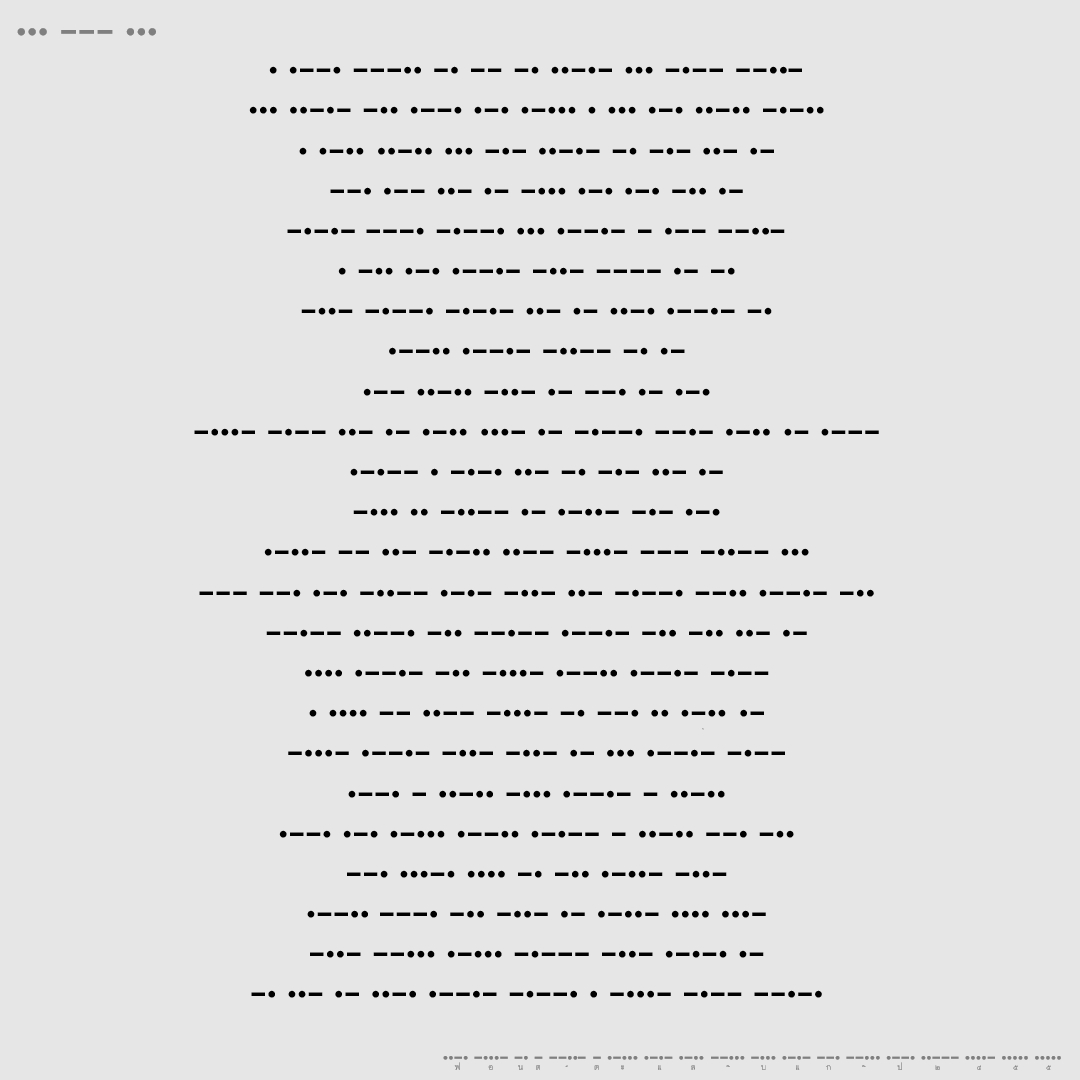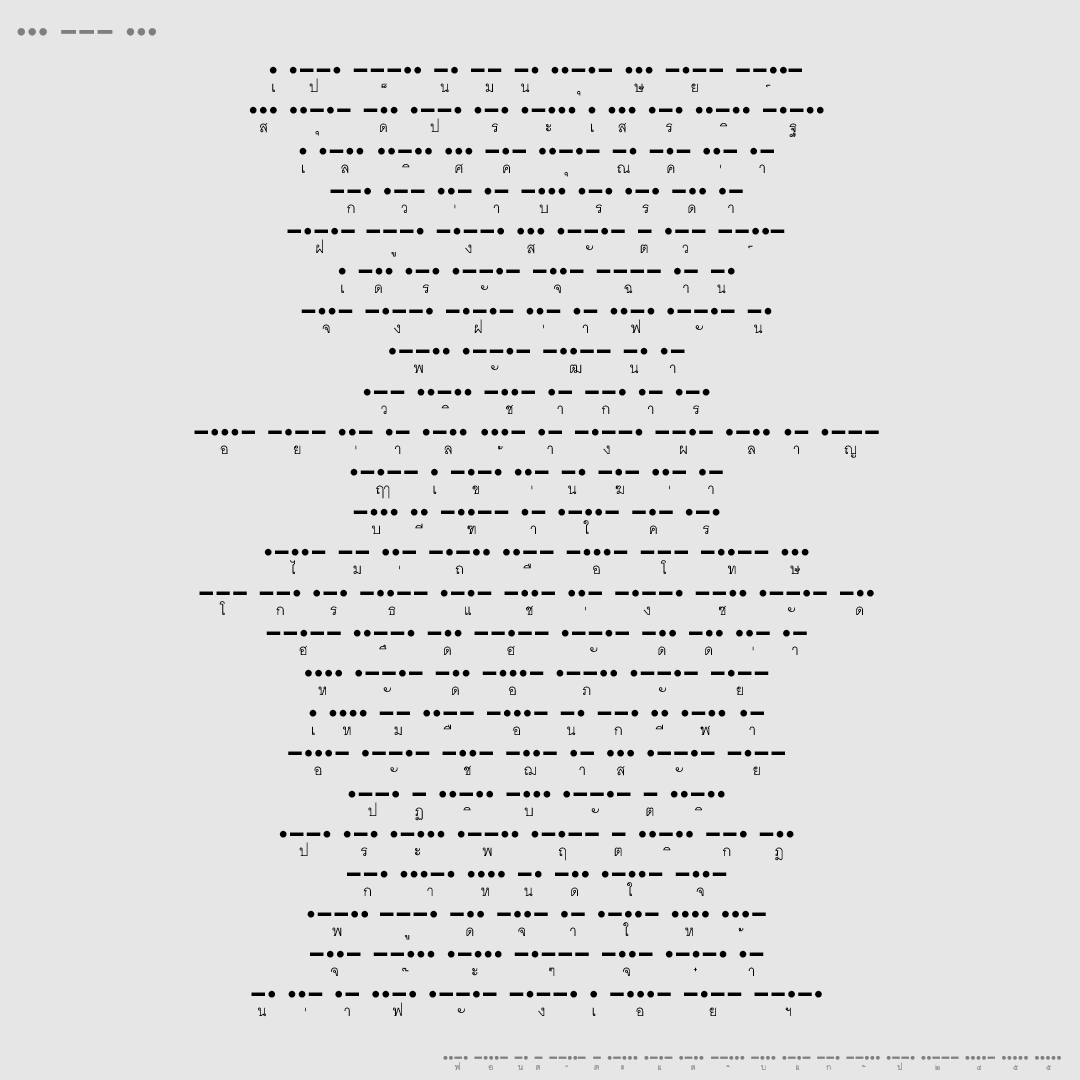
ฟอนต์ ตะแล๊บแก๊ป๒๔๕๕
"จุด จุด ขีด จุด   ขีด ขีด ขีด   ขีด จุด   ขีด   ขีด ขีด จุด จุด ขีด"  ตะแล๊บแก๊ป..ฟอนต์ที่อ่านไม่ออก แต่ก็อ่านออกอยู่นะ รหัสมอร์สภาษาไทย (คล่องแคล่วแล้วให้กด bold)
แพนแกรม ที่คุ้นเคย